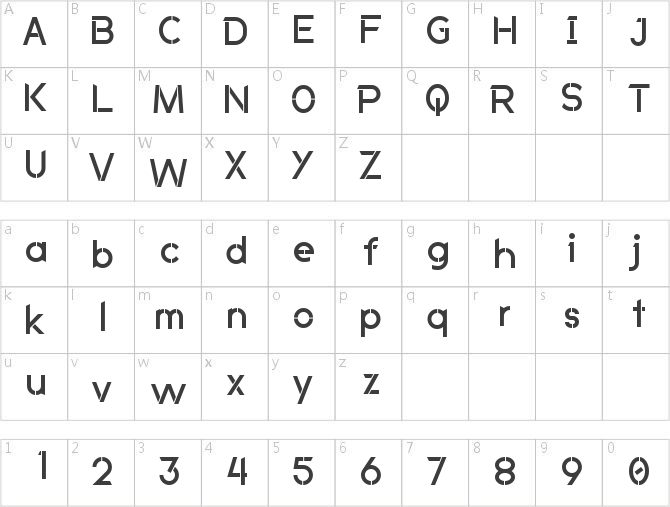
字體名稱: Anklada
Anklada Novaz regular
Anklada Novaz regular介紹
Anklada Novaz regular字體字庫是一款讓人賞心悅目、百看不厭的英文字體,適合各類廣告和產品包裝設計應用,字體大小0.04MB,格式為ttf字體,上傳用戶是小籃子,作者/版權方為未知